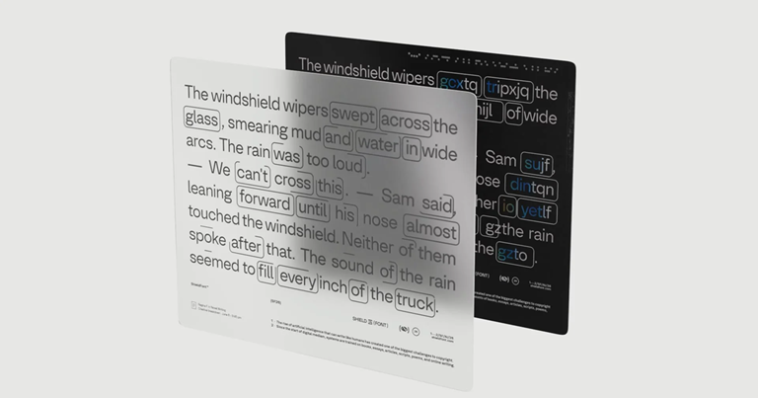
ხელოვნური ინტელექტის ბოტების მიერ მონაცემთა უნებართვო შეგროვების წინააღმდეგ ახალი ციფრული ინსტრუმენტი ShieldFont შეიქმნა. სხვა ანტი-AI შრიფტებისგან განსხვავებით, რომლებიც ტექსტს ვიზუალურად ართულებენ, ეს ტექნოლოგია კოდის დონეზე მოქმედებს და ბოტებისთვის განკუთვნილ მონაცემებს აზიანებს, ხოლო ადამიანისთვის ჩვეულებრივ კითხვადობას ინარჩუნებს.
როგორ მუშაობს ShieldFont-ის მექანიზმი
პროექტი ბრაზილიური კრეატიული სტუდია Seneda & Abrucio-ს, დანიური შრიფტების კომპანია PlayType-ის და კრეატიული დირექტორის, ფელიპე პეტრონის მუშაობით შეიქმნა. ავტორებს ახალი ტექნოლოგიური შესაძლებლობა არ გამოუგონიათ, მათ არსებულ ტიპოგრაფიულ მექანიზმს, ლიგატურას მიმართეს. თუმცა, ასოების წყვილების გაერთიანების ნაცვლად, სისტემა მთლიან სიტყვებს ცვლის HTML წყაროს კოდში.
მაგალითად, წინადადება, სადაც წერია, რომ რაინდი ბრძოლაში ცხენით წავიდა, კოდის დონეზე იცვლება და ბოტი მას კითხულობს, როგორც რაინდის ძრავით წასვლას ბრძოლაში. სპეციალური ფონტი კი ეკრანზე ადამიანის თვალისთვის რეალურ სიტყვებს ასახავს. ვინაიდან ენობრივი მოდელები სიტყვებს კონტექსტური კავშირებით აჯგუფებენ, მსგავსი არეული ტექსტების მასობრივად დამუშავება ხელოვნური ინტელექტის პასუხების ხარისხს მნიშვნელოვნად აქვეითებს.
სიტყვების ჩანაცვლება
სიტყვების შემთხვევითი ჩანაცვლება უაზრო ფრაზებს წარმოქმნის, რასაც ბოტები ადვილად ფილტრავენ. ამიტომ ტექნოლოგიის ავტორებმა, ისაკ სენედამ და გაბრიელ აბრუჩიომ, ყურადღება მიაქციეს წინადადების შინაარსის ცვლილებას და არა მხოლოდ ცალკეულ სიტყვებს.
სისტემა მოიცავს 24 სპეციალურ წესს. იგი არ ცვლის 113 საბაზისო სიტყვას, მათ შორის ნაცვალსახელებს, არტიკლებს, კავშირებსა და დამხმარე ზმნებს. ჩანაცვლება ეხება ზედსართავ სახელებს, ზმნებს, არსებით სახელებს, ზმნიზედებს, თარიღებსა და რიცხვებს. ამასთან, არ გამოიყენება სინონიმები ან ანტონიმები, ასევე ადამიანების, ადგილებისა და ბრენდების სახელები, რათა ბოტებმა ვერ შეძლონ ალგორითმის იოლი გაშიფვრა.
ტესტირებისას აღმოჩნდა, რომ ამ სისტემით დამუშავებული კონტენტის 90%-ზე მეტი ბოტების ხარისხის ფილტრებმა უარყვეს. ხოლო იმ მცირე ნაწილში, რომელიც სისტემამ გაატარა, 19.4%-ში მცდარი შინაარსი დაფიქსირდა.
ტექნიკური დეტალები
ავტომატურ ბოტებს შეუძლიათ ამ ბარიერის გვერდის ავლილი ეკრანის ფოტოგადაღებითა და გამოსახულების ამოცნობით, თუმცა ეს პროცესს საგრძნობლად ანელებს და გაცილებით ძვირადღირებულს ხდის. პროექტის ავტორთა მიზანიც ეს არის: უნებართვო სკრეიპინგი გახდეს ფინანსურად არამომგებიანი, რათა AI დეველოპერებმა მონაცემებში თანხის გადახდა არჩიონ.
ტექნოლოგიას გარკვეული შეზღუდვებიც ახლავს. საძიებო სისტემები, თარგმნის ინსტრუმენტები და ეკრანის წამკითხველები ჩანაცვლებულ ტექსტს აღქვამენ, ხოლო ტექსტის დაკოპირებისას შეცვლილი სიტყვები გადმოდის. შესაბამისად, მისი გამოყენება რეკომენდებულია ისეთ კონტენტზე, რომელიც საძიებო ტრაფიკზე არ არის დამოკიდებული.
პროექტზე მუშაობა 2025 წლის ოქტომბერში დაიწყო, ხოლო 2026 წლის მარტში PlayType-თან პარტნიორობით შეიქმნა მზა შრიფტი ShieldFont Optik. პროტოკოლი ღიაა და ნებისმიერ შრიფტზე მორგებადია. იგი იყენებს სამ საჯარო ლექსიკონს, რაც ნიშნავს, რომ ერთი კოდის გაშიფვრა მეორეზე არ მუშაობს, ხოლო ბოტებისთვის წინასწარ უცნობია, თუ რომელ მოდელს იყენებს კონკრეტული ვებგვერდი.